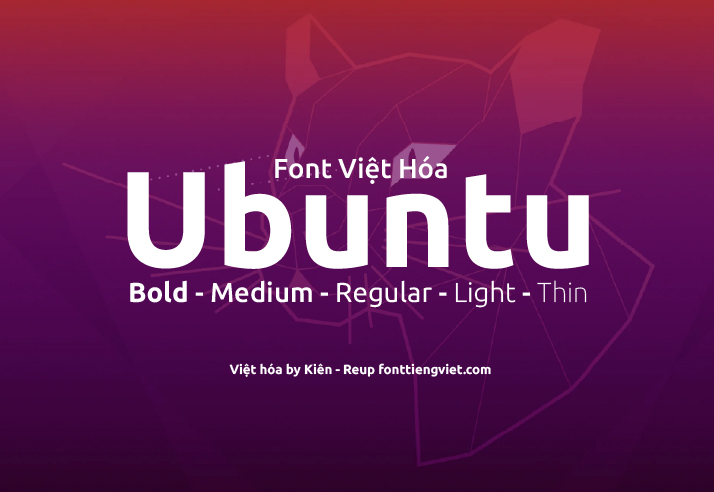
Trong thế giới thiết kế đồ họa, Font việt hóa Ubuntu đã trở thành một biểu tượng quen thuộc nhờ sự kết hợp hoàn hảo giữa tính hiện đại và khả năng hiển thị rõ nét. Được thiết kế bởi xưởng chữ Dalton Maag danh tiếng cho hệ điều hành Ubuntu, bộ Font Chữ này mang phong cách Humanist đặc trưng với các đường cong mượt mà, giúp văn bản trở nên dễ đọc và thân thiện hơn. Khi được việt hóa đầy đủ, Ubuntu cho phép người dùng tại Việt Nam thoải mái sáng tạo nội dung mà không lo lỗi font hay thiếu ký tự tiếng Việt đặc thù.
Ưu điểm nổi bật của Font việt hóa Ubuntu
Khả năng hiển thị xuất sắc trên mọi thiết bị
Đặc trưng của Ubuntu là độ rõ nét cực cao ngay cả ở kích thước nhỏ. Điều này giúp các bạn học sinh dễ dàng trình bày bài tập lớn hoặc các thầy cô thiết kế giáo án điện tử mà vẫn giữ được sự chuyên nghiệp. Khoảng cách giữa các con chữ được tinh chỉnh hợp lý, tạo cảm giác thoáng đãng và dễ chịu cho mắt người xem.
Đa dạng phong cách thiết kế
Với đầy đủ các định dạng từ Light, Regular đến Bold Italic, bạn có thể ứng dụng linh hoạt vào việc thiết kế slide thuyết trình, banner truyền thông hoặc giao diện website. Sự đồng nhất trong phong cách giúp sản phẩm của bạn trông hiện đại và có tính hệ thống cao hơn bao giờ hết.
Kết luận về bộ Font việt hóa Ubuntu
Có thể khẳng định rằng, việc sử dụng Font việt hóa Ubuntu là lựa chọn thông minh cho những ai tìm kiếm sự cân bằng giữa thẩm mỹ và công năng. Dù bạn là một lập trình viên cần phông chữ rõ ràng để viết code hay một nhà thiết kế đang tìm kiếm sự mới mẻ, bộ font này chắc chắn sẽ làm hài lòng mọi nhu cầu khắt khe nhất. Đừng bỏ lỡ cơ hội tải về và trải nghiệm Font Miễn Phí, Font Việt Hóa, Font việt hóa Ubuntu ngay hôm nay để nâng tầm các dự án sáng tạo của chính mình.